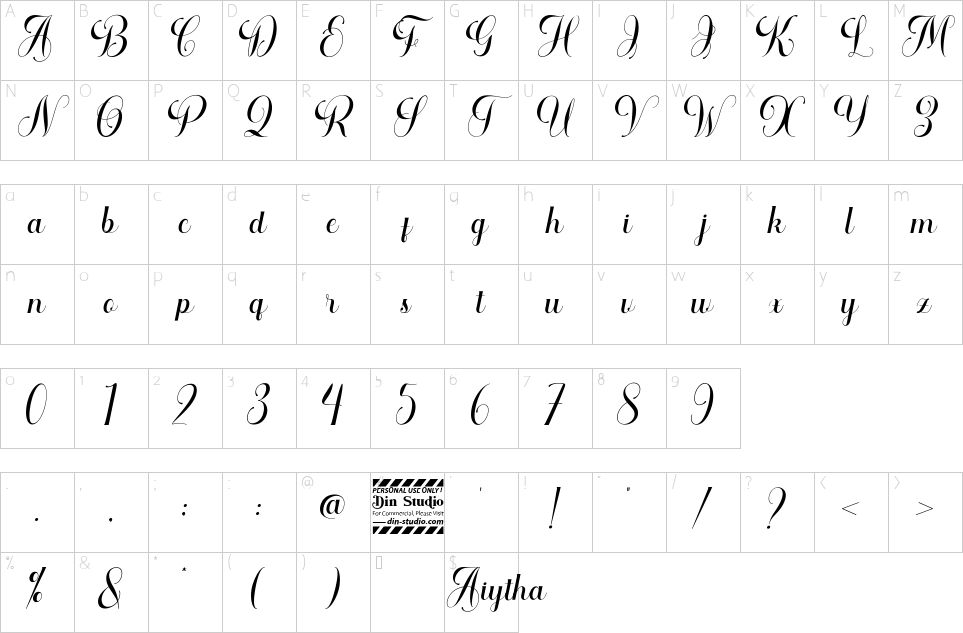
Descubra a beleza da Aiytha font, perfeita para designers e criativos do Brasil. Desenvolvida por Donis Miftahudin, esta fonte oferece um toque único e sofisticado para seus projetos digitais. Aiytha foi projetada para atender aos requisitos gráficos da região, oferecendo uma variedade de linhas e tamanhos para se adequar a qualquer tipo de design. Descubra por que esta fonte tem sido popular entre designers, graças à sua variedade de aplicações e facilidade de uso. Aiytha já foi baixada por 333 usuários, evidenciando seu valor e popularidade. Para quem busca uma fonte de qualidade e versátil sem comprometer o tempo, Aiytha é uma ótima escolha. Baixe já e experimente o poder desta fonte.